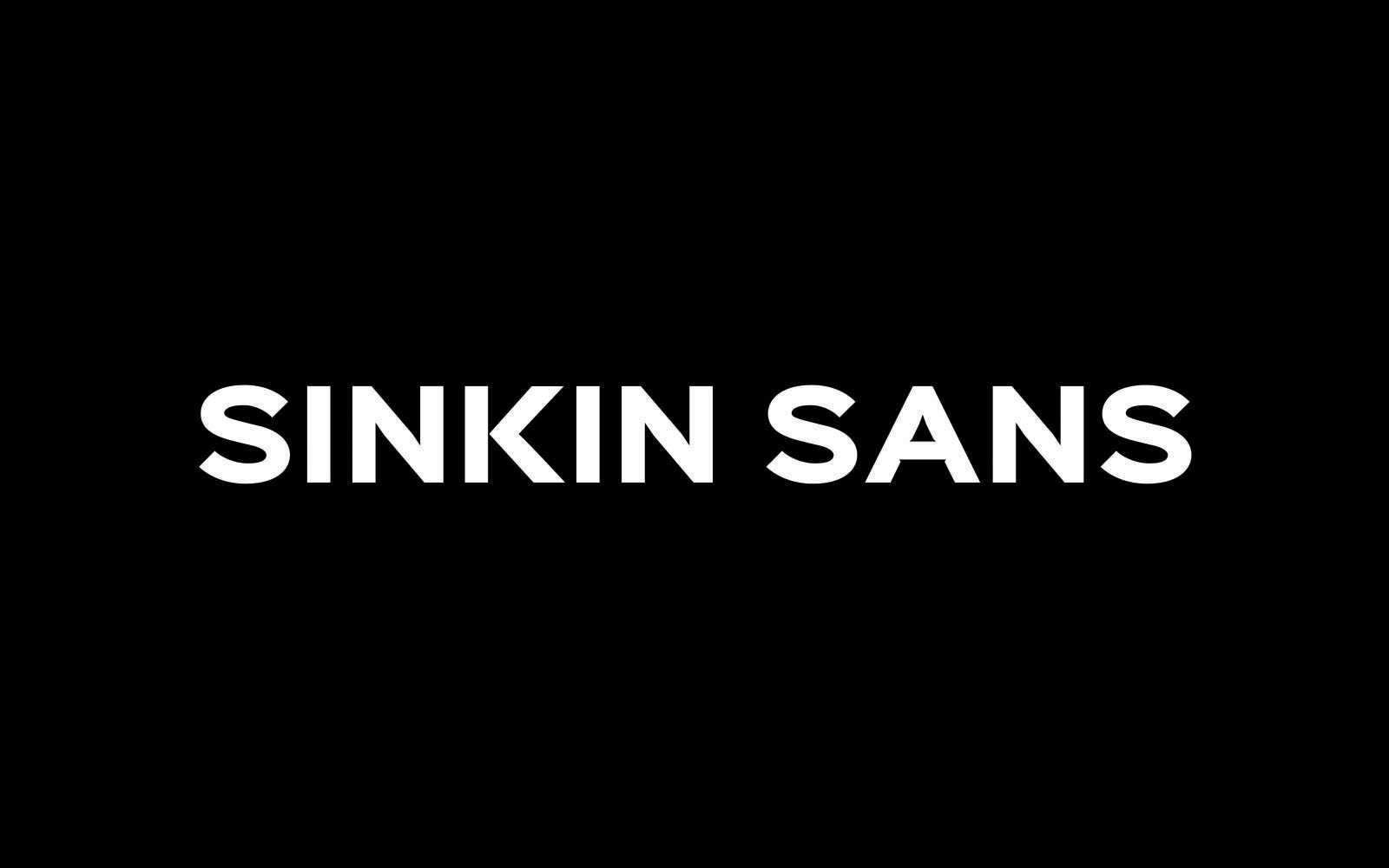
Sinkin Sans Typeface
A página de download do recurso gráfico ‘Sinkin Sans Typeface’ apresenta uma fonte sans-serif simples, legível e elegante, oferecida em todas as 9 pesos padrões para web. Este recurso gráfico, criado para redefinir a página web da K-Type, incorpora pequenos e inconspícuos notões que entram nos ângulos da interseção de traços, criando destaque nos cantos congestionados. Esses incisões também tornam os ângulos retos mais agudos e melhoram a definição em caracteres mais complexos. A fonte é ideal para sites responsivos, oferecendo uma combinação harmônica de simplicidade e sofisticação, adequada para qualquer aplicação de design gráfico online.